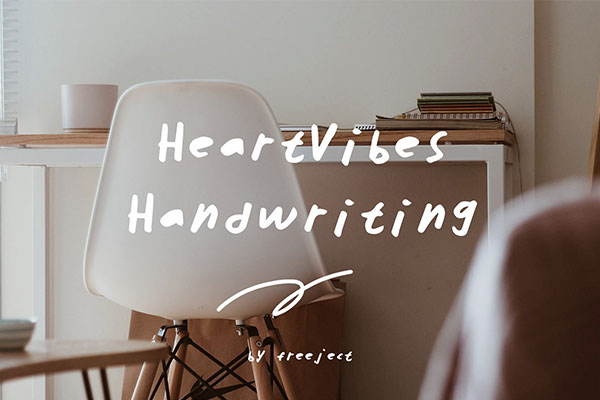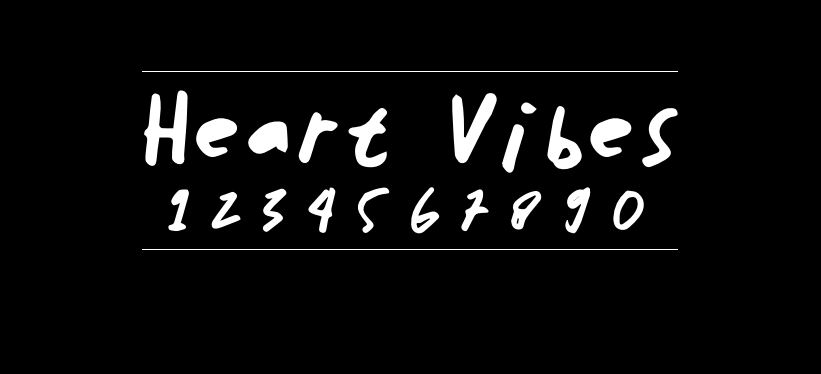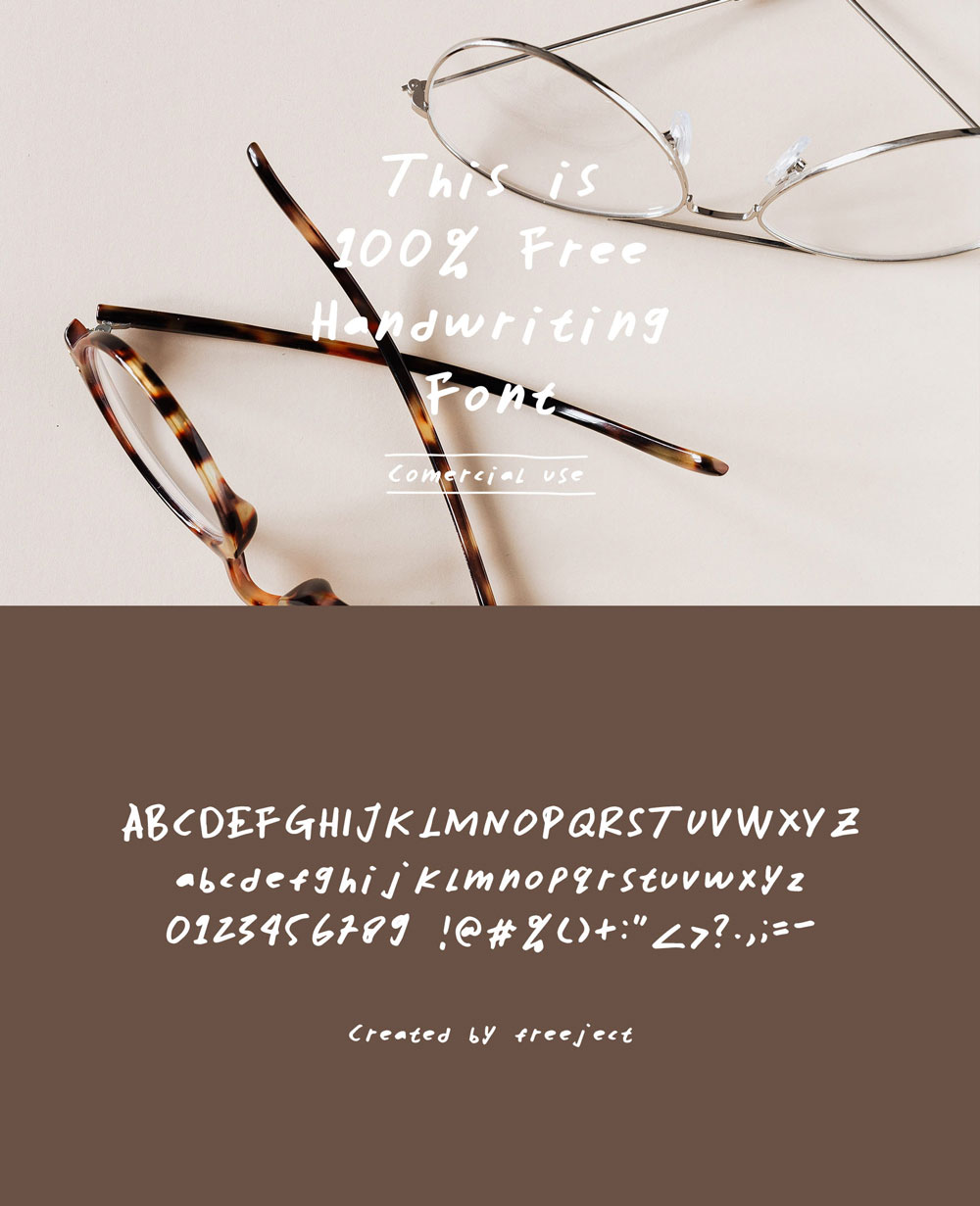
Heart Vibes
Heart vibes 是freejet推出的一款手写风格免费字体,该字体是使用手写技术制作的。如果你在你的设计中使用它,它看起来与实际的手写文本非常相似,它可能看起来不像是一种字体。但是,真的,这种心形字体看起来像是一种自然的手写字体。这种字体适合想要随意或友好呈现的设计。然而,一些旧的、复古的或夏季的氛围也适用于它。
Heart vibes 字体有大写、小写、数字和标点符号。但是,标点符号可能不完整。尽管如此,这款字体制作精美,因此可以完美地完成您的设计。您可以将它用于段落和显示字体。自定义大小以区分它,同时将其用于部分和标题。和上面的预览一样,可以一起使用。除此之外,将其用于广告或活动也可能是一个好主意。
使用它创建您的创意设计项目。它可能是独特的,对观众来说看起来很新鲜。此外,它是一种多功能字体,可以将此字体用于任何项目。您可以使用它创建许多东西。